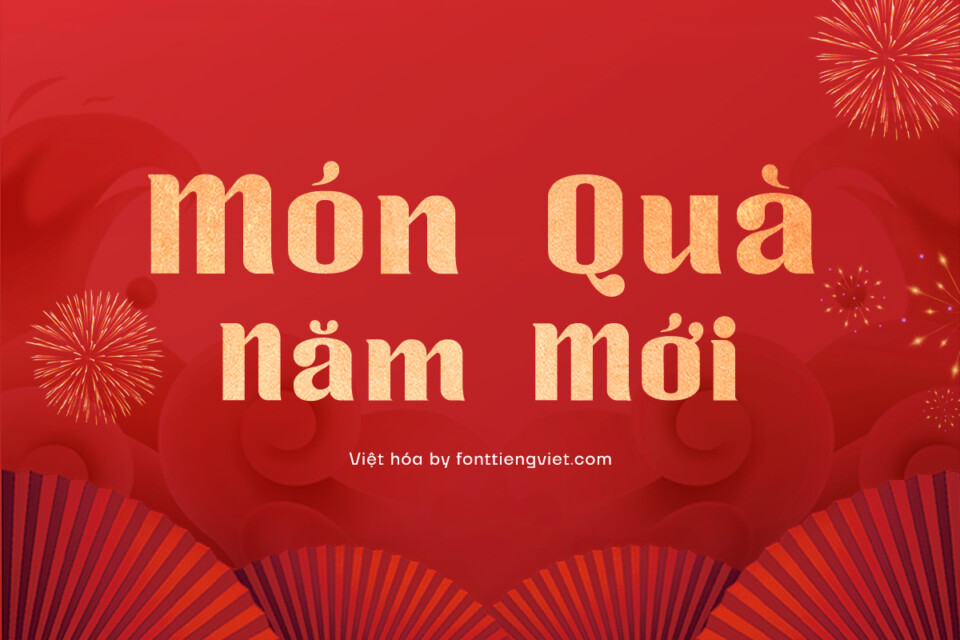
Font Việt hóa 1FTV VIP Zoika – Font tết
Font Việt hóa 1FTV VIP Zoika – Font tết: Sự lựa chọn hoàn hảo cho thiết kế năm mới rực rỡ
Giới thiệu về bộ Font Việt hóa 1FTV VIP Zoika – Font tết
Mỗi dịp Tết đến Xuân về, nhu cầu tìm kiếm những bộ Font Miễn Phí mang đậm bản sắc văn hóa Việt Nam lại trở nên sôi động hơn bao giờ hết. Trong số các bộ phông chữ nổi bật hiện nay, Font Việt hóa 1FTV VIP Zoika – Font tết đang khẳng định được vị thế riêng biệt nhờ sự kết hợp hài hòa giữa nét vẽ truyền thống và phong cách hiện đại. Đây là bộ font được thiết kế tỉ mỉ, giúp người dùng truyền tải trọn vẹn không khí ấm áp, sum vầy của ngày Tết cổ truyền thông qua các ấn phẩm thiết kế. Việc sử dụng đúng phông chữ không chỉ nâng cao tính thẩm mỹ mà còn giúp thông điệp chúc mừng năm mới trở nên gần gũi và ý nghĩa hơn đối với mọi thế hệ người Việt.
Đặc điểm nổi bật của Font Việt hóa 1FTV VIP Zoika – Font tết
Phong cách thiết kế độc đáo và linh hoạt
Bộ Font Việt hóa 1FTV VIP Zoika – Font tết sở hữu những đường nét uốn lượn uyển chuyển, gợi liên tưởng đến những nét bút lông của các ông đồ thời xưa nhưng đã được tinh chỉnh để trông thanh thoát hơn. Điểm mạnh của bộ font này chính là sự đa dạng trong cách ứng dụng. Bạn có thể dễ dàng sử dụng nó cho các tiêu đề chính trên banner, bìa thiệp chúc mừng hoặc thậm chí là các đoạn trích ngắn trong video kỷ niệm. Với bảng mã ký tự đầy đủ các dấu tiếng Việt, người dùng sẽ không gặp phải tình trạng lỗi hiển thị hay thiếu ký tự khi soạn thảo nội dung dài.
Tối ưu hóa cho các ấn phẩm truyền thông sự kiện
Đối với các bạn học sinh hay thầy cô giáo thường xuyên tham gia trang trí báo tường, làm slide thuyết trình về lễ hội truyền thống, Font Việt hóa 1FTV VIP Zoika – Font tết thực sự là một trợ thủ đắc lực. Độ tương phản giữa các nét thanh và nét đậm được tính toán kỹ lưỡng, giúp chữ viết luôn sắc nét dù in ấn trên khổ lớn hay hiển thị trên màn hình điện thoại. Màu đỏ, vàng và xanh lá cây là những tông màu cực kỳ phù hợp khi kết hợp cùng bộ phông này, tạo nên một tổng thể thị giác vô cùng bắt mắt và rộn ràng không khí lễ hội.
Cách ứng dụng Font Việt hóa 1FTV VIP Zoika – Font tết hiệu quả nhất
Sáng tạo thiệp chúc mừng và bao lì xì
Ứng dụng phổ biến nhất của Font Việt hóa 1FTV VIP Zoika – Font tết chính là thiết kế các mẫu bao lì xì độc quyền. Bạn có thể kết hợp font chữ này với các họa tiết như hoa mai, hoa đào, bánh chưng để tạo ra những sản phẩm mang đậm dấu ấn cá nhân. Ngoài ra, khi viết những lời chúc như An Khang Thịnh Vượng hay Vạn Sự Như Ý, bộ font này sẽ giúp câu chữ trở nên sang trọng và mang tính nghệ thuật cao hơn hẳn các phông chữ hệ thống thông thường.
Thiết kế banner và trang trí không gian lớp học
Trong môi trường giáo dục, việc sử dụng Font Việt hóa 1FTV VIP Zoika – Font tết để thiết kế các bảng tin chúc mừng năm mới hoặc các phông nền sự kiện ngoại khóa sẽ kích thích sự hứng thú của học sinh. Sự chân thực trong từng nét chữ giúp các em thêm yêu quý những giá trị văn hóa dân tộc. Để đạt hiệu quả tốt nhất, bạn nên căn chỉnh khoảng cách giữa các chữ cái một cách vừa phải, tránh làm các nét uốn lượn chồng chéo lên nhau gây khó đọc.
Tổng kết về bộ font chữ Tết đặc sắc